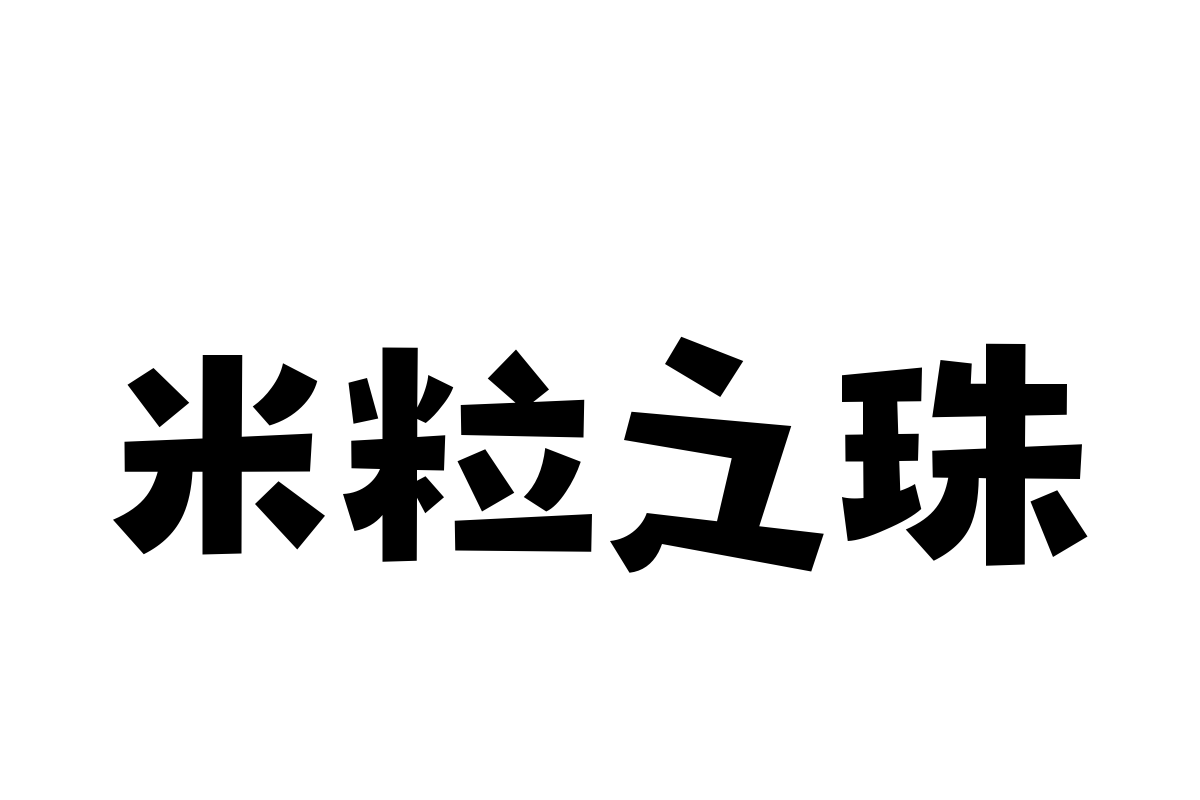
汉仪永字椰子树繁体字体是一款具有现代感和科技感的字体,适用于各种设计场景。这款字体的特点包括:
1. 简洁明了:汉仪永字椰子树繁体字体线条流畅,字形简洁,易于阅读和理解。
2. 现代感:该字体采用了现代的设计元素,如斜线和曲线,给人一种时尚、前卫的感觉。
3. 科技感:字体中的数字和符号采用现代科技风格,如点阵数字和箭头等,增加了字体的科技感。
4. 适应性强:汉仪永字椰子树繁体字体适用于各种设计场景,如广告、海报、网页设计等。
5. 可定制性:用户可以根据自己的需求对字体进行个性化定制,如更改字体大小、颜色等。
总之,汉仪永字椰子树繁体字体是一款适合现代设计场景的字体,具有简洁明了、现代感、科技感等特点,适用于各种设计场景。